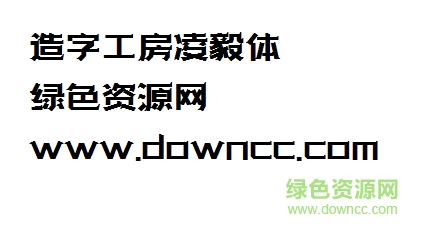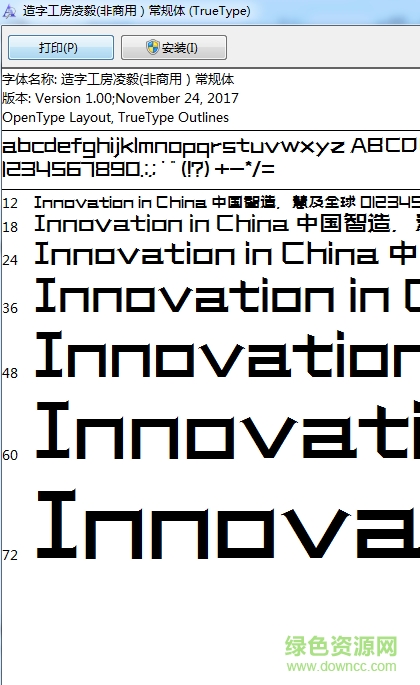
造字工房凌毅體字體
造字工房凌毅體整體風(fēng)格一絲不茍粗黑醒目,可用于各大標(biāo)題的設(shè)計(jì),此字體為常規(guī)體非商用,特此推薦給學(xué)習(xí)字體的朋友們,歡迎收藏下載!
造字工房凌毅體字體造型規(guī)整,富于力度,給人以簡(jiǎn)潔爽朗的現(xiàn)代感,有較強(qiáng)的視覺(jué)沖擊力,這種個(gè)性的字體,適合于機(jī)械科技等主題。
造字工房凌毅體